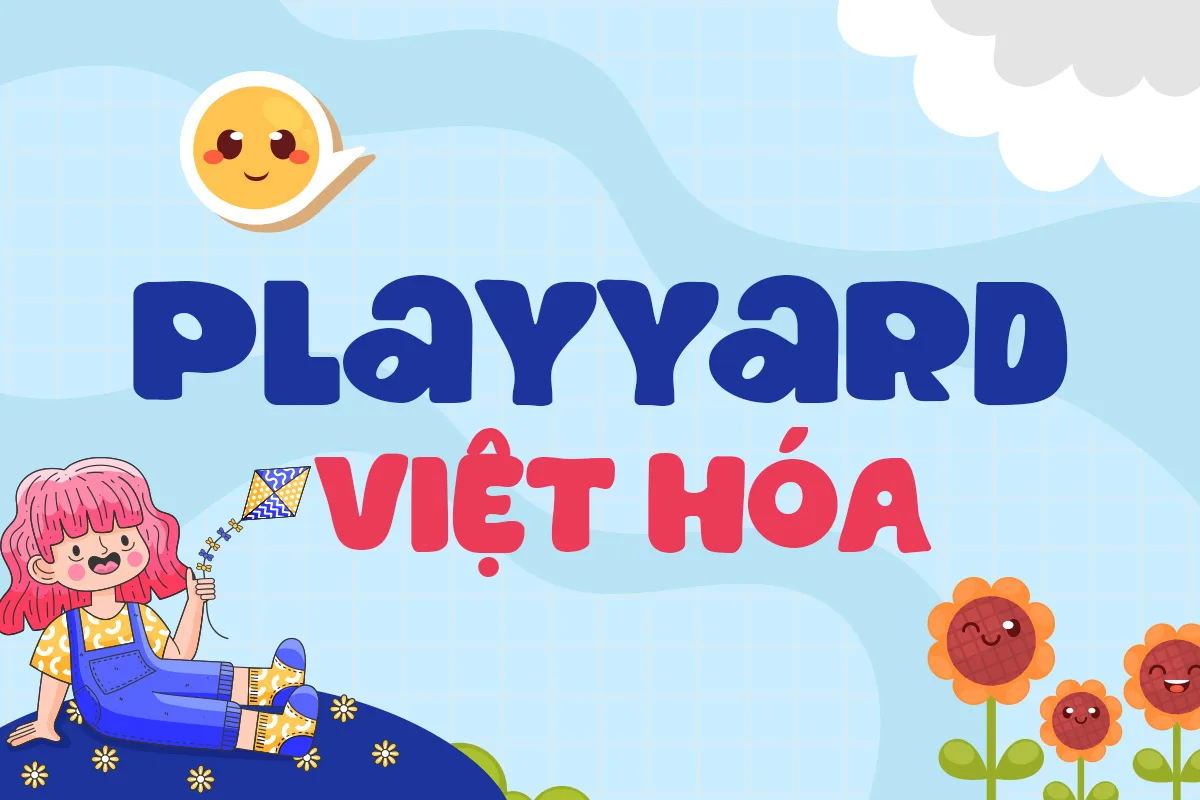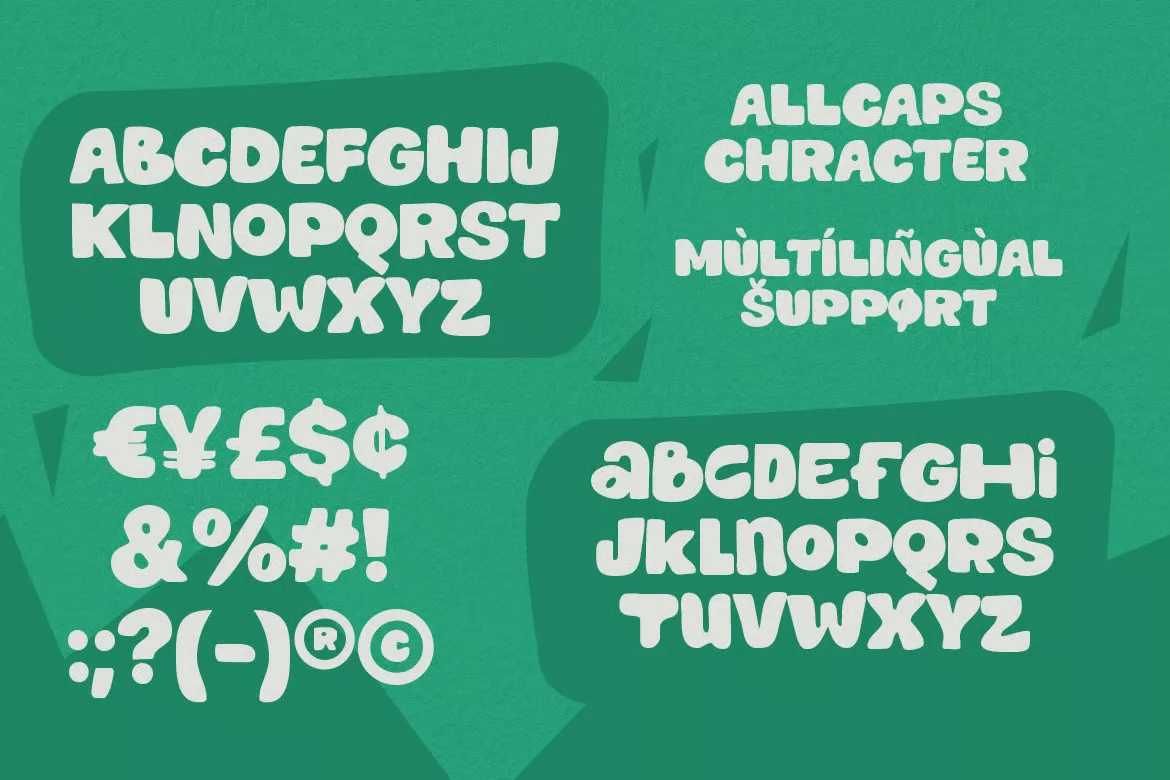
DVN Playyard Việt hóa – Font chữ bong bóng siêu đáng yêu
DVN Playyard là một phông chữ không chân mang phong cách bong bóng vô cùng ngộ nghĩnh, nổi bật với những đường nét bo tròn mũm mĩm và cấu trúc chữ nhảy múa tự do. Thiết kế này phá vỡ các khuôn mẫu cứng nhắc thông thường để tạo ra một tổng thể sinh động, mang lại cảm giác cực kỳ thân thiện, tràn đầy sức sống và năng lượng tích cực ngay từ cái nhìn đầu tiên.
Với bộ ký tự đồ sộ bao gồm đầy đủ số, dấu câu, các biểu tượng đặc biệt cùng khả năng hỗ trợ đa ngôn ngữ, DVN Playyard đáp ứng linh hoạt nhiều nhu cầu thiết kế khác nhau. Đây là sự lựa chọn hoàn hảo để làm bừng sáng các dự án hướng tới trẻ em, thiết kế bao bì bánh kẹo, truyện tranh, poster sự kiện vui nhộn hay bất kỳ ấn phẩm truyền thông nào cần một điểm nhấn tinh nghịch và phá cách.